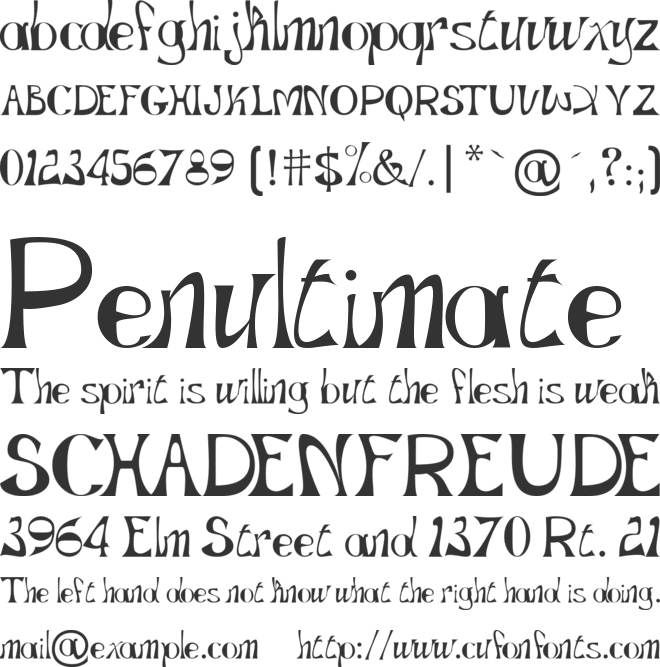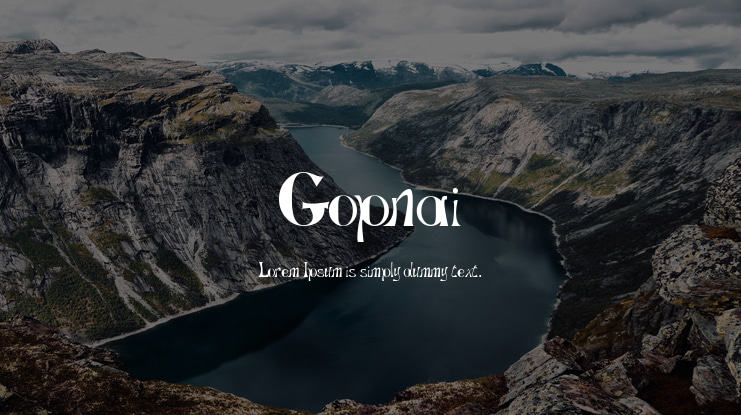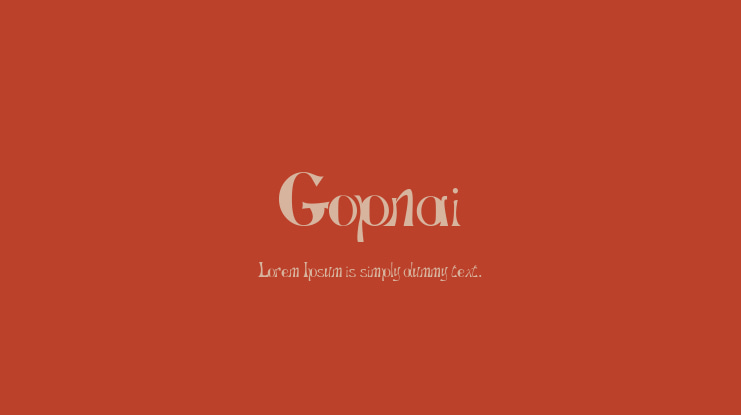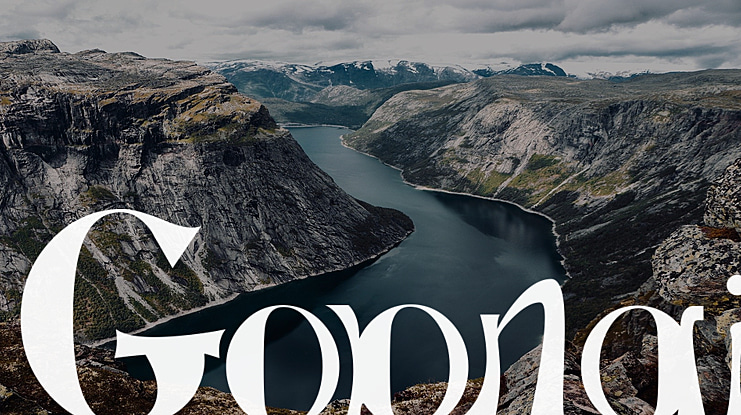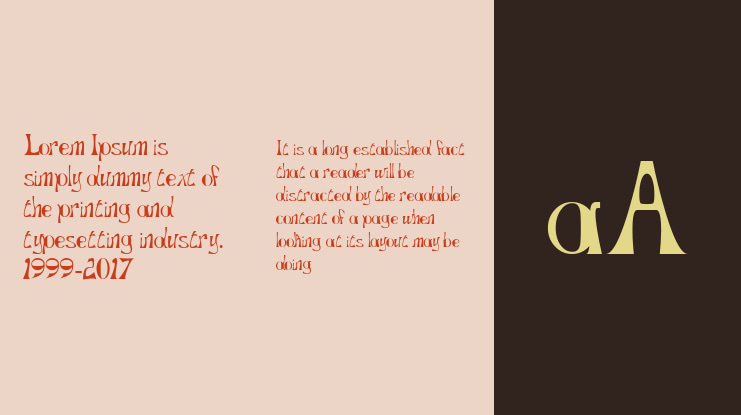
Gopnai Font
Gopnai Droogie Con esta idea me refiero a una fuente de compañia, bajo el concepto de Anthony Burgess's en "A Clockwork Orange".
Símbolos estén juntos, pero sin llegar a tocarse.
Para uso en títulos y subtitulos y/o otros usos (Dependiendo para qué se requiera).